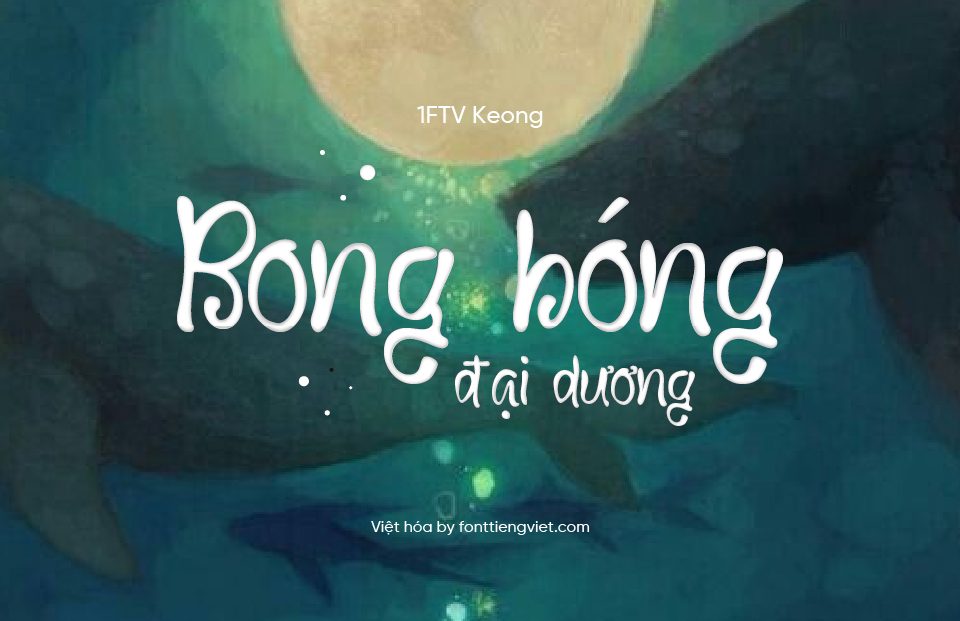
Font Việt hóa 1FTV Keong
Tải Ngay Font Việt hóa 1FTV Keong – Nét Chữ Vui Nhộn Cho Thiết Kế
Giới thiệu về Font Việt hóa 1FTV Keong
Trong thế giới đồ họa hiện đại, việc lựa chọn một Font Miễn Phí phù hợp đóng vai trò then chốt tạo nên sự thành công cho sản phẩm. Font Việt hóa 1FTV Keong là một bộ phông chữ mang phong cách vui tươi, năng động và tràn đầy năng lượng. Được tinh chỉnh kỹ lưỡng để hỗ trợ đầy đủ tiếng Việt, 1FTV Keong giúp người dùng dễ dàng truyền tải thông điệp một cách rõ ràng mà vẫn giữ được nét cá tính riêng biệt. Đây là sự lựa chọn tuyệt vời cho các dự án thiết kế mang tính chất giáo dục, bìa sách thiếu nhi hoặc các banner quảng cáo sự kiện trường học.
Ưu điểm nổi bật của Font Việt hóa 1FTV Keong
Phong cách thiết kế độc đáo
Đặc điểm nhận dạng của Font Việt hóa 1FTV Keong chính là các đường nét bo tròn và cấu trúc chữ dày dặn. Điều này tạo cảm giác gần gũi, thân thiện, đặc biệt phù hợp với đối tượng học sinh và trẻ em. Khi sử dụng bộ chữ này, các nhà thiết kế có thể dễ dàng tạo ra những tiêu đề nổi bật và thu hút thị giác ngay từ cái nhìn đầu tiên. Bên cạnh đó, tính ứng dụng của nó cực kỳ cao, từ việc làm slide bài giảng đến thiết kế áo lớp hay thiệp mời sự kiện.
Tương thích và tối ưu hóa
Bộ Font Việt hóa 1FTV Keong không chỉ đẹp về thẩm mỹ mà còn được tối ưu hóa về kỹ thuật. Các ký tự tiếng Việt như dấu hỏi, dấu ngã được đặt vị trí chuẩn xác, tránh tình trạng lỗi font khi gõ văn bản dài. Bạn có thể sử dụng mượt mà trên nhiều phần mềm khác nhau như Photoshop, Canva hay Microsoft Office. Việc cài đặt cũng rất đơn giản, chỉ cần vài thao tác chuột là bạn đã có thể bắt đầu sáng tạo.